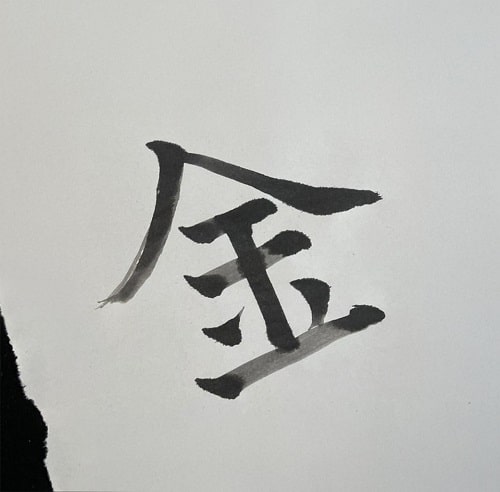
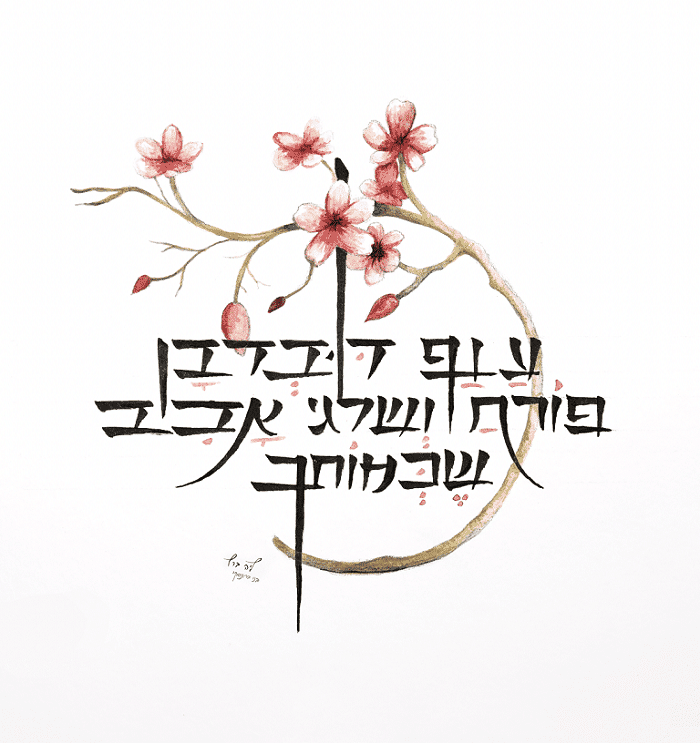
הקליגרפיה – אמנות הכתיבה בכתב יד – היא הרבה מעבר לכלי ויזואלי להעברת מידע. היא שפה חזותית, ביטוי לתרבות ומקור השראה אינסופי. קליגרפיה סינית ויפנית, שתיהן בעלות שורשים עתיקים ועתירות משמעות ועומק, השפיעו באופן משמעותי וכזה שיש לתת עליו את הדעת על התפתחות הכתיבה והעיצוב החזותי ברחבי העולם לכל אורך השנים עד העת המודרנית, ועד בכלל.
הטיפוגרפיה המערבית, כפי שאנו מכירים אותה היום בצורה של טיפוגרפיה אומנותית, התפתחה וצמחה מתוך מסורת ארוכה של כתיבה – אולי לא תאמינו – בכתב יד. רנסאנס הכתיבה, תקופה של פריחה עיצובית באירופה, היה סימן מפנה משמעותי בעיצוב האותיות. אמנים ומשעתקים חיפשו דרכים לשכלל ולשדרג את כתב היד שלהם, להפוך אותו לאלגנטי יותר, ברור יותר וגם יפה ואומנותי יותר.
במקביל, במזרח אסיה פיתחו קליגרפיה סינית ויפנית שפות חזותיות עשירות ומורכבות. כל סימן, כל משיחת מכחול, כל קו או יציאה מהקווים – נטענו במשמעות עמוקה. האסתטיקה המזרח אסיאתית הדוגלת בהרמוניה, איזון וחיבור לטבע, השפיעה על עיצוב האותיות והסמלים בדרכים שונות ומגוונות גם בטכניקת קליגרפיה עברית.
הקשר בין המזרח למערב אף פעם לא היה חד-כיווני, וכך גם היה בנושא בו אנו עוסקים. סוחרים, משלחות דיפלומטיות ומסעות של אמנים יצרו גשרים תרבותיים, והעבירו עימם ממקום למקום רעיונות חדשים. אמנים מערביים שנחשפו באחת הדרכים האלה לקליגרפיה המזרח אסיאתית, התאהבו ומצאו בה מקור השראה חדש. הם הושפעו עמוקות מהקו העדין והאלגנטי, מהשימוש בניגודים בין שחור לבן, ומהיחס המיוחד למרחב הלבן.
אחד המאפיינים הבולטים של הקליגרפיה המקובלת במזרח אסיה הוא ההקשר בין הכתיבה לציור. האמנים המקומיים ראו בכל סימן ואות יצירת אמנות בפני עצמה. לגישה הזו שלהם הייתה השפעה ניכרת על עיצוב האותיות בעולם המערבי. היא הובילה להתפתחות של הטיפוגרפיה האומנותית, שבה כל אות היא בעצם יצירה בפני עצמה, החותרת להיות מרהיבה בזכות עצמה.
ההשפעה של קליגרפיה גותית והקליגרפיה המזרח אסיאתית על הטיפוגרפיה המערבית המודרנית ניכרת בכל מקום.
פונטים רבים המשמשים כל אחד מאיתנו בעיצובים הגרפיים שלנו בפרסום ובמדיה הדיגיטלית מבוססים על עקרונות עיצוביים שנלקחו מעולמות הקליגרפיה.
הקשר בין טיפוגרפיה לזהות תרבותית הוא חזק ועמוק. השאלת אלמנטים מעיצובים זרים מעלה שאלות מעניינות על הזהות התרבותית ועל הגבולות בין השונה והדומה. הטמעת אלמנטים מהקליגרפיה המזרחית בטיפוגרפיה המערבית היא תהליך מורכב, המצריך רגישות תרבותית והבנה עמוקה של שתי המסורות.
השפעת הקליגרפיה המזרח אסיאתית על עיצוב פונטים מודרניים היא מעבר לאלמנטים ויזואליים כמו קווים עדינים, ניגודים בין שחור לבן והקשר בין כתיבה לציור.
היא השפיעה גם על הגישה העיצובית עצמה:
שילוב אלמנטים מהקליגרפיה המזרח אסיאתית בעיצוב פונטים מודרניים הוא תהליך רגיש הדורש כבוד והבנה עמוקה של התרבות המקורית. כדי לעשות זאת בצורה נכונה, ניתן לנקוט בגישות הבאות: